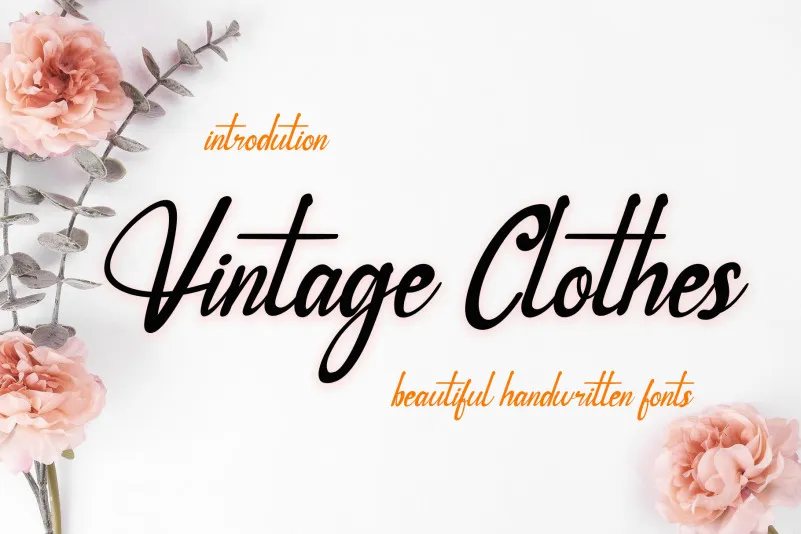
Vintage Clothes Font – Download Grátis
Esta é uma elegante e fluida fonte escrita a mão. Mantém seus traços clássicos do calligrafismo enquanto mantém um toque contemporâneo e moderno. Esta fonte encantadora se tornará o toque final para qualquer projeto, elevando-o ao próximo nível. O designer kateengciu criou uma fonte a mão com traços delicados que vão agridoce à mente, fazendo-a perfeitamente adequada tanto para uso em design gráfico como em projetos digitais. Adotar esta fonte é um convite sincero para experimentar novas possibilidades e expressões únicas através do design visual.